今回は、味岡伸太郎著の『味岡伸太郎 書体講座』を紹介します。
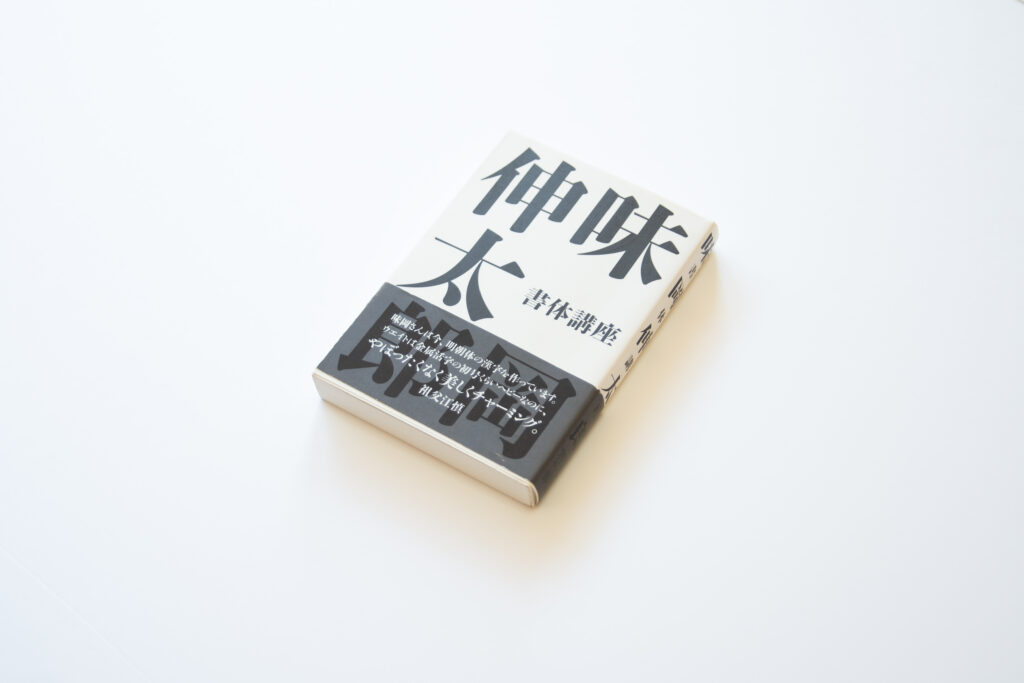
本書はグラフィックデザイナーでもあり明朝体フォント「味明」シリーズを手がけた味岡伸太郎氏による書体、タイポグラフィに関する文章が収録されています。書体を作るに至った経緯、字体や書体、著作権等について論じられています。本全体が著者の手掛けた書体で組まれていて、書体の見本帳にもなっています。
「縦組横組考」の章では縦組が主流だった時代から、横組が増えて今では当たり前にそれを受け入れていることについて、歴史や文化を汲んだ日本の書体やタイポグラフィのあり方がどうあってほしいかを批判を交えながら書かれています。著者のように書体やタイポグラフィを批評する目を持ち、論じることができるのは重要で、自分はその言葉を持ち合わせているのかと顧みながら読みました。フォントメーカーで仕事をする私にとってはかなり耳が痛い話も多く、新しい視点を得られた本でした。